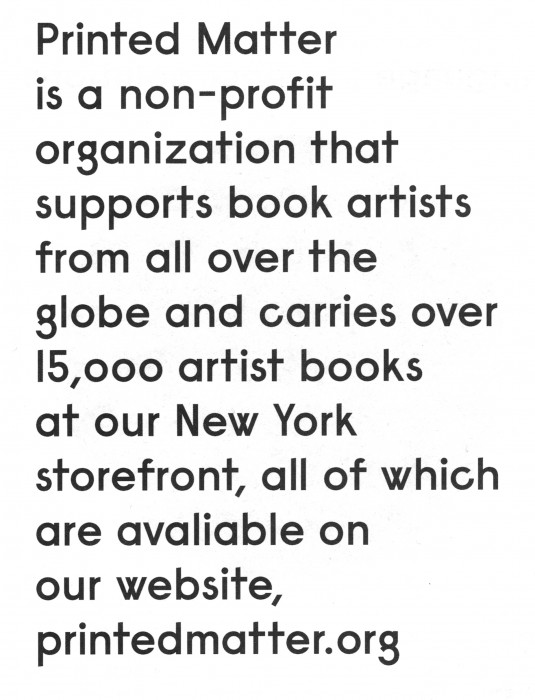
Schöne Schrift – aber welche?
Irgendwie eine Mischung aus Kabel und Futura, aber schön ...  :-?
WOW! Mann! Wie hast Du das denn so schnell rausgekriegt?
Naja, sie ist in meinen kleinen, grauen Zellen einfach so aufgepoppt. Keine Ahnung, wie die das machen. Ich gebe zu, dass ich aber auch ein Geek bin.  :rockon:
faustregel:
zeistgeist + krude - myfonts - lineto = colophone foundry
Schön auf den Punkt gebracht!